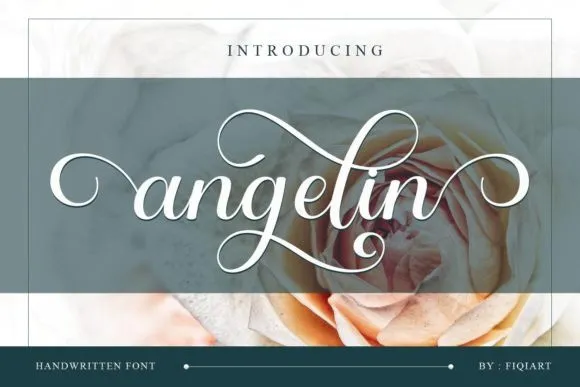
A fonte ‘Angelin Font’ é uma criação do designer fiqiart09, apresentando-se com traços cuidadosamente delineados e personagens afiados e divertidos. Ela se destaca especialmente para projetos que exigem um estilo personalizado, como convites de casamento, cartões de agradecimento, identidades visuais, cartazes de aniversário ou até mesmo logotipos. Suas linhas limpas e desenhada com uma inclinação chamativa tornam ‘Angelin Font’ perfeita para qualquer tipo de projeto gráfico, oferecendo um toque único e encantador. Seu sistema PUA (Unicode Private Use Area) permitirá que você acceda facilmente a todas as formas e feixes da fonte, garantindo uma variedade ilimitada de possibilidades criativas. Esta font é ideal para quem quer dar um toque especial a seus projetos visuais com um design único e desenhado por mãos humanas. Com ‘Angelin Font’, você pode criar mensagens que chamam atenção, seja em cartões de casamento ou identidade visual de empresas, sua mensagem terá uma aparência singular e inovadora.